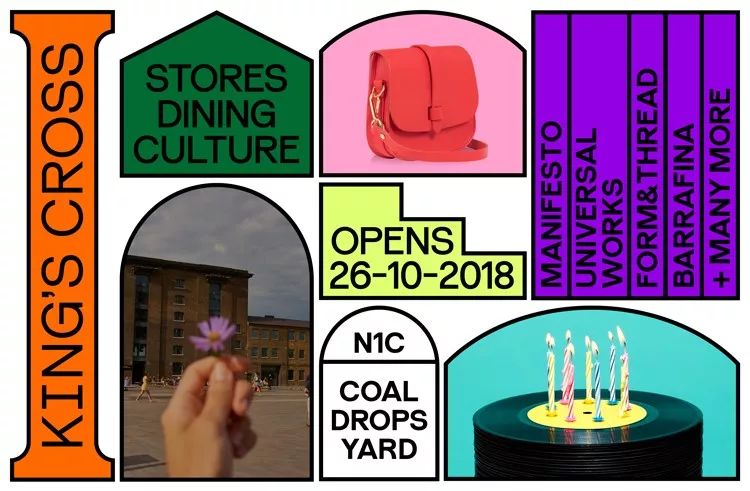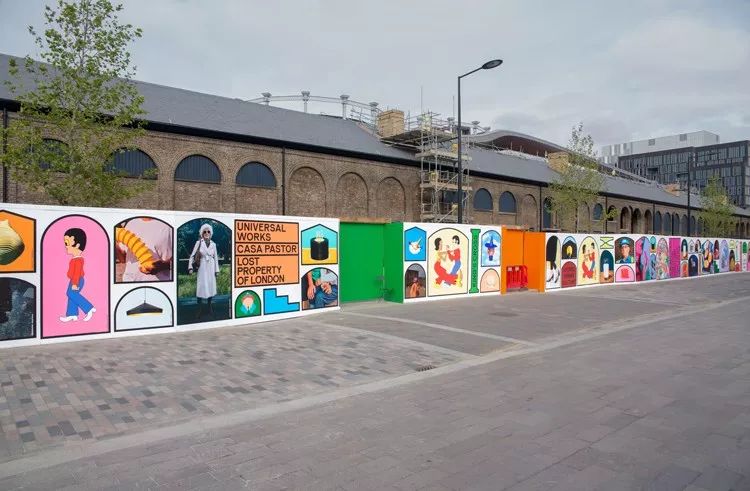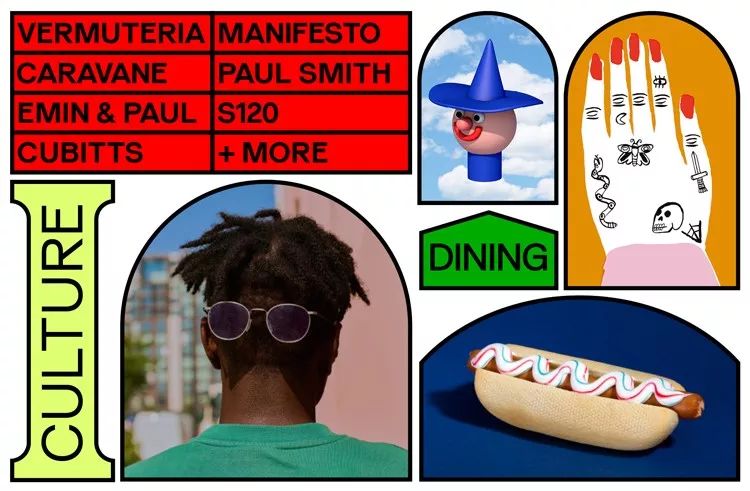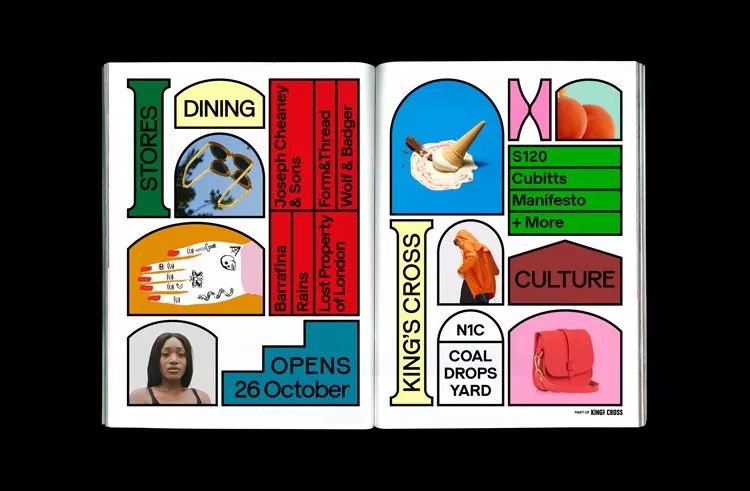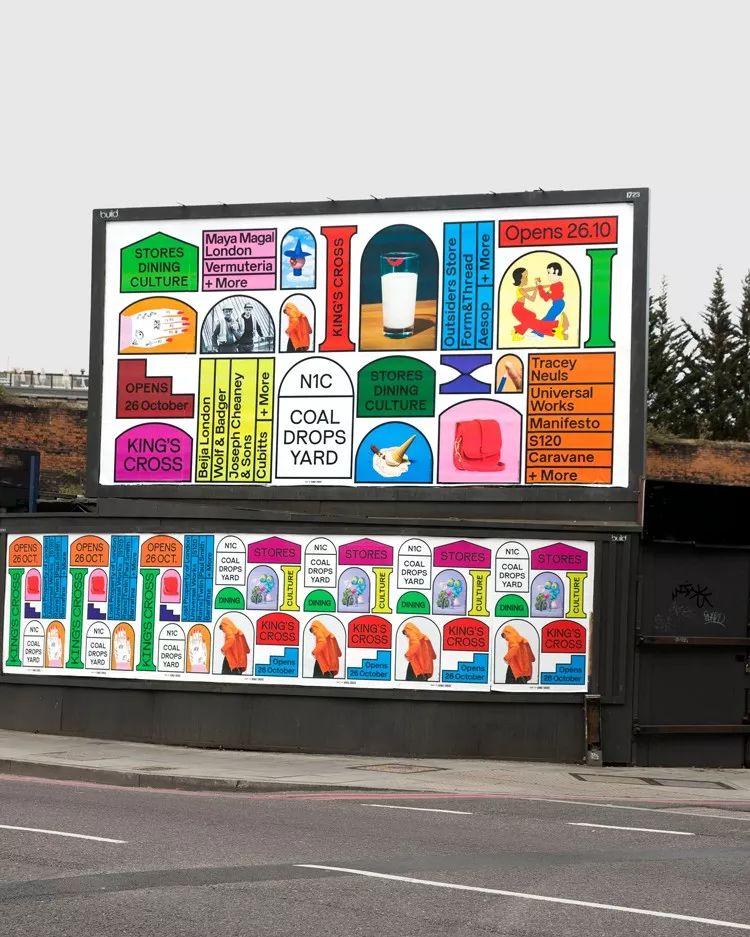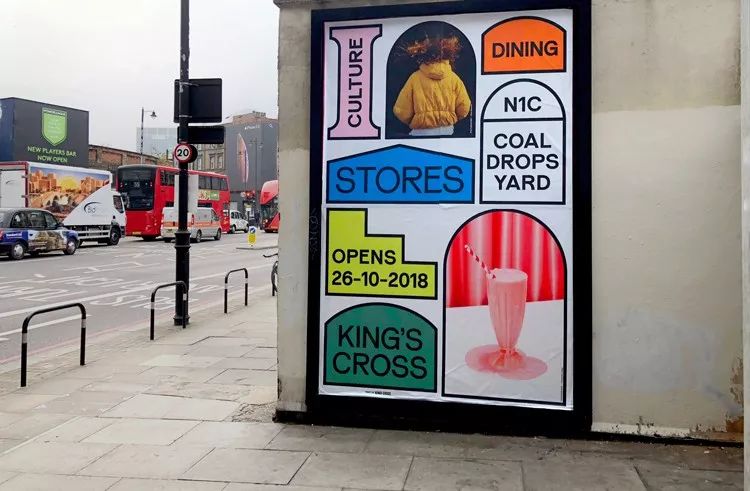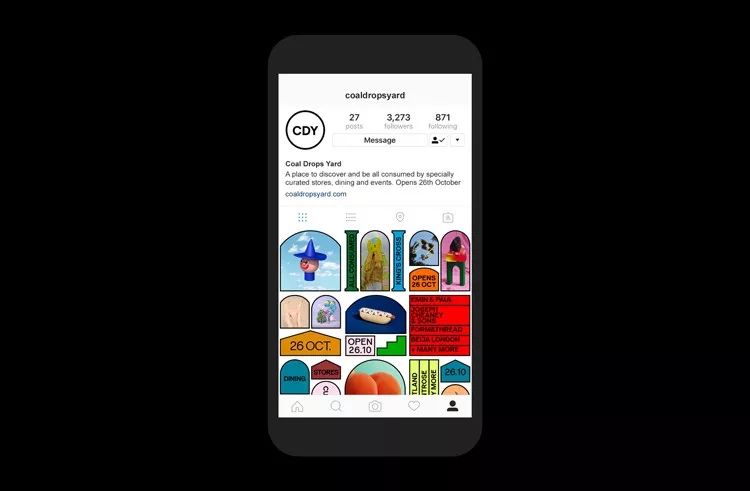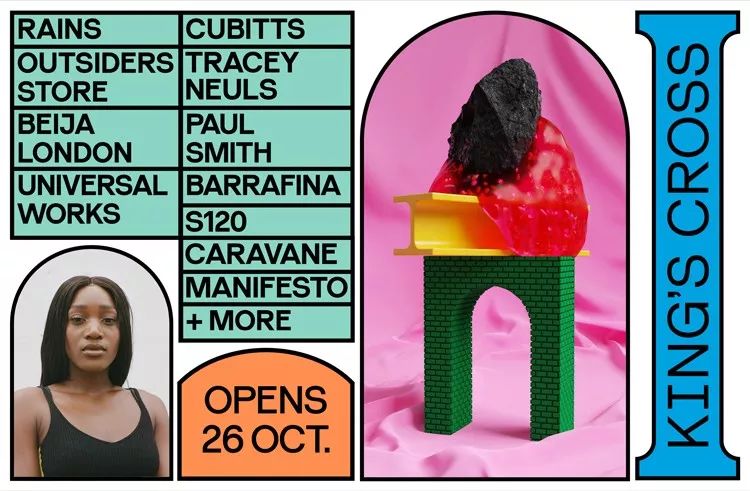
购物中心的品牌视觉设计案例分享
2018年10月,伦敦北部新开了一个大型购物休闲区——Coal Drops Yard购物中心。这个由设计师托马斯赫斯维克(Thomas Heatherwick)设计的项目,拥有伊索(Aesop)和Cubitts(眼镜品牌)等品牌的高端商店、Barrafina等广受好评的餐厅,以及即将开业的Facegym健身房等更为新奇的设施。
Droga5广告公司设计的品牌标识旨在将这里作为“重新定义消费主义”、“向所有人开放”的另类文化胜地进行销售。
Droga5考虑了如何与国王十字街区(King’s Cross)接轨,使煤渣场从“同类”购物中心脱颖而出,以及如何处理奢侈品商店与公共空间之间的冲突。
但Coal drop Yard的品牌诉求并非如此。这个新的购物区被Droga5广告公司赋予了一个色彩缤纷、兼收并蓄的品牌形象,这里充斥着各种形状、竖向文字和随意摆置的摄影作品,来表现国王十字车站的“多样性”,同时打破了“企业”购物中心的传统外观。
Droga5的艺术总监克里斯查普曼(Chris Chapman)表示:
“你能在任何地区,无论是伦敦、悉尼还是美国,看到千篇一律的购物中心。”
“我们想证明,人们在这里可以有不同的体验,零售体验和非零售体验。”
他补充说:“这里有社区会议场所,也有带盒饭的地方,这样人们就不必去高档餐厅或商店了。”
“我们试图用一种折中的方式,在视觉上传达这种多样性。”
查普曼表示,该品牌由摄影和图形拍摄组成,由当地艺术家设计,目的是展示Coal Drops Yard是如何成为一个“公共空间”的,并且在这里“每个人都有自己的东西”。
“空间的设计想让每个人都感到受欢迎,”他说。“这是一个透气、宽敞、开放的空间,没有门卫把守的封闭入口。”
“这意味着顾客能感觉自己是国王十字街区的一部分。”
Droga5委托不同的艺术家拍摄与国王十字街区有关的事物,比如能反映这里的生活方式的照片和当地人的照片,同时也创作了“非消费主义”主题。比如有盒饭的图片来展示人们在空间里可以做什么。
视觉设计中在使用彩色调色板的同时,还采用了由Colophon字体开发公司创建的无衬线黑色字体。
文字和文案保持在最小值,比如品牌名称或活动的三个主要宣传词“商店、餐饮和文化”,但在出现文案的地方,文案也以黑色为背景,用彩色背景包围,然后用黑色勾勒出矩形。
查普曼说,主字体是“很基本的字体”,但工作室通过创建不同版本的字母和字符,以及不同的笔划粗细,赋予了它“多样性”。
查普曼说,文字和图像在垂直和水平方向上同时出现,这是广告海报上常见的信息结构的离经叛道,目的是让访问者的眼睛“漫游”,而不是给他们一个有指向性的方向。这一设计的目的是为了表现出Coal Drops Yard的布局是鼓励游客去探索,而不是被引导去“硬买”。
查普曼表示:“我们希望减少对企业品牌的控制,制定尽可能少的规则。”
“我们必须相信,这个标识足够强大,可以任意玩。”
他表示:“通常情况下,竞选海报的层次结构很容易地让人知道眼睛看向哪里。”
查普曼说:“这是关于重新定义消费主义。”
“去Coal Drops Yard肯定是一种消费方式,但我们希望人们更注意自己是如何消费的。”
从购物到空间的设计再到它的历史,去那里是一种全方位的体验而不是在你的手机上无意识地买东西。查普曼说,虽然Coal Drops Yard的目标是有眼光的消费者,但这个品牌活动的目的是告诉公众,每个人都可以享受它。该品牌活动包括在国王十字地铁站(King’s Cross tube station)旁边的购物区周边铺设平面广告牌。
他表示:“我们希望尽可能让它显得不那么精英化,不那么中产阶级化。”
“Coal Drops Yard就是这样——它是一个购物中心。在那里有一些相当高档的商店,我们许多人买不起——但它也是一个适合每个人的地方。”
查普曼表示:“我们真诚地代表我们的客户,欢迎大家,并尽可能地平易近人。”“我们不想让它感觉像某个冰冷、封闭、时髦的地方——它必须感觉像一个公共空间。”
Coal Drops Yard品牌视觉现已在平面材料(如广告海报、促销书籍、国王十字车站的平面广告牌)和数字平台(如Coal Drops Yard网站和社交媒体)上推广。